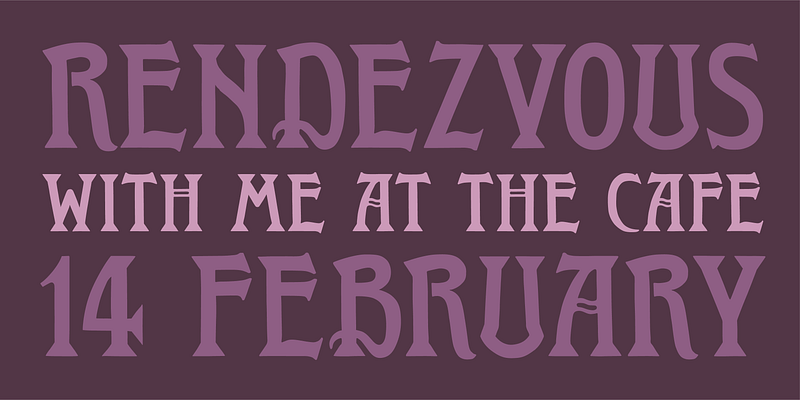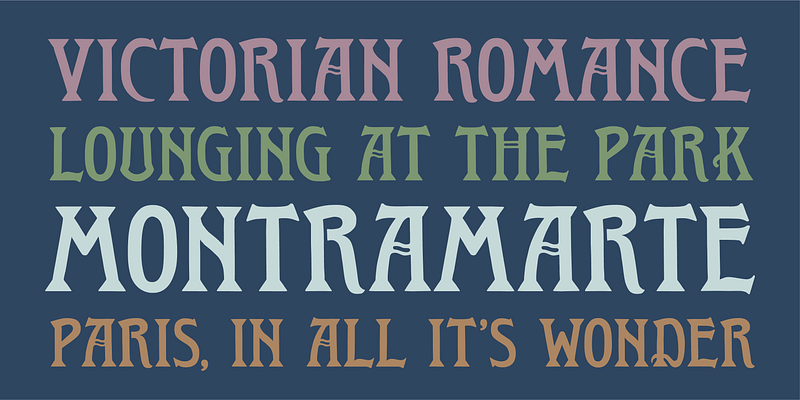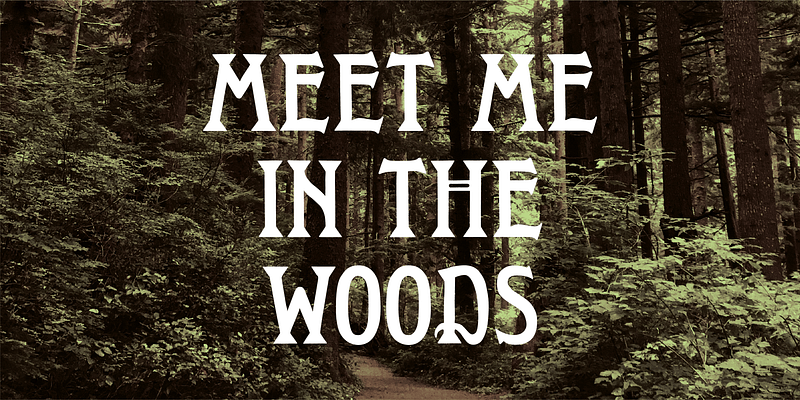
Wood Type Revival
Wood Type Revival está descubriendo y preservando el tipo de letra en madera histórico, convirtiéndolo fielmente en fuentes digitales para diseñadores modernos. Todos los tipos de letra de Wood Type Revival se crean a partir de prensas manuales originales del siglo XIX. El resurgimiento del tipo de letra en madera es el resultado del exitoso proyecto Kickstarter de impresoras de impresión tipográfica y los barbudos diseñadores Matt Griffin y Matt Braun. Juntos trabajan para enriquecer el paisaje tipográfico moderno reintroduciendo tipos de letras olvidados en el mundo digital.